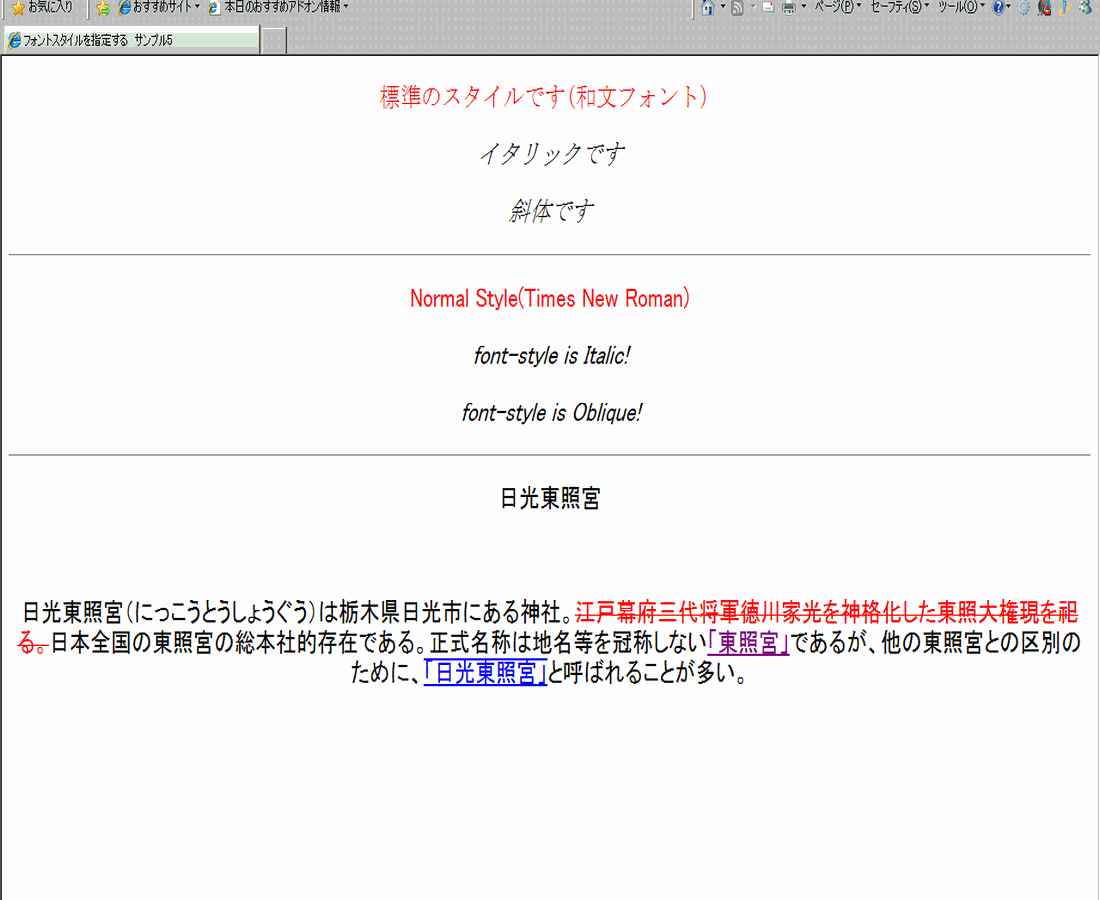
| プロパティ名 | 値 | 適用対象 | 継承 |
|---|---|---|---|
| font-style: | フォントのスタイル | すべての要素 | 有り |
| text-decoration: | 装飾名 | すべての要素 | なし |
| 値 | 説明 | |
|---|---|---|
| フォントの スタイル | italic | イタリック体で表示。 |
| oblique | 斜体で表示。 | |
| normal | 普通の状態で表示(デフォルト)。 | |
| 装飾名 | underline | 文字列に下線を引く。 |
| overline | 文字列に上線を引く。 | |
| line-through | 文字列に取り消し線を引く。 | |
| blink | 文字列を点滅させる。 | |
| none | 文字列を装飾のない状態で表示(デフォルト)。 |
font-styleプロパティは、フォントを斜体にするかどうかを、text-decorationプロパティは、フォントの装飾を指定します。フォントのスタイルには、italic、oblique、normalのどれかを指定します。
斜体は通常のフォントを斜めに傾けたもので、イタリック体は専用にデザインされた物です。イタリック体がない時は、斜体で表示されます。
text-decorationプロパティは、文字列に装飾を付けます。装飾名にはunderline、overline、line-through、blink、noneを指定します。それぞれの文字に対して、「下線」「上線」「取消線」を付け、「blink」は文字を「点滅」させます。これらの値は、半角スペースで区切って、同時に複数指定できます。指定の順序は任意です。
斜体を標準に戻すには、font-styleプロパティにnormalを、装飾をなくすには、text-decorationプロパティにnoneを指定します。
斜体は通常のフォントを斜めに傾けたもので、イタリック体は専用にデザインされた物です。イタリック体がない時は、斜体で表示されます。
text-decorationプロパティは、文字列に装飾を付けます。装飾名にはunderline、overline、line-through、blink、noneを指定します。それぞれの文字に対して、「下線」「上線」「取消線」を付け、「blink」は文字を「点滅」させます。これらの値は、半角スペースで区切って、同時に複数指定できます。指定の順序は任意です。
斜体を標準に戻すには、font-styleプロパティにnormalを、装飾をなくすには、text-decorationプロパティにnoneを指定します。
●斜体とイタリック体は異なるフォントですがプラウザでは違いを区別しておらず、同じように表示されます。
●blinkは、Internet Explorerには対応していません。